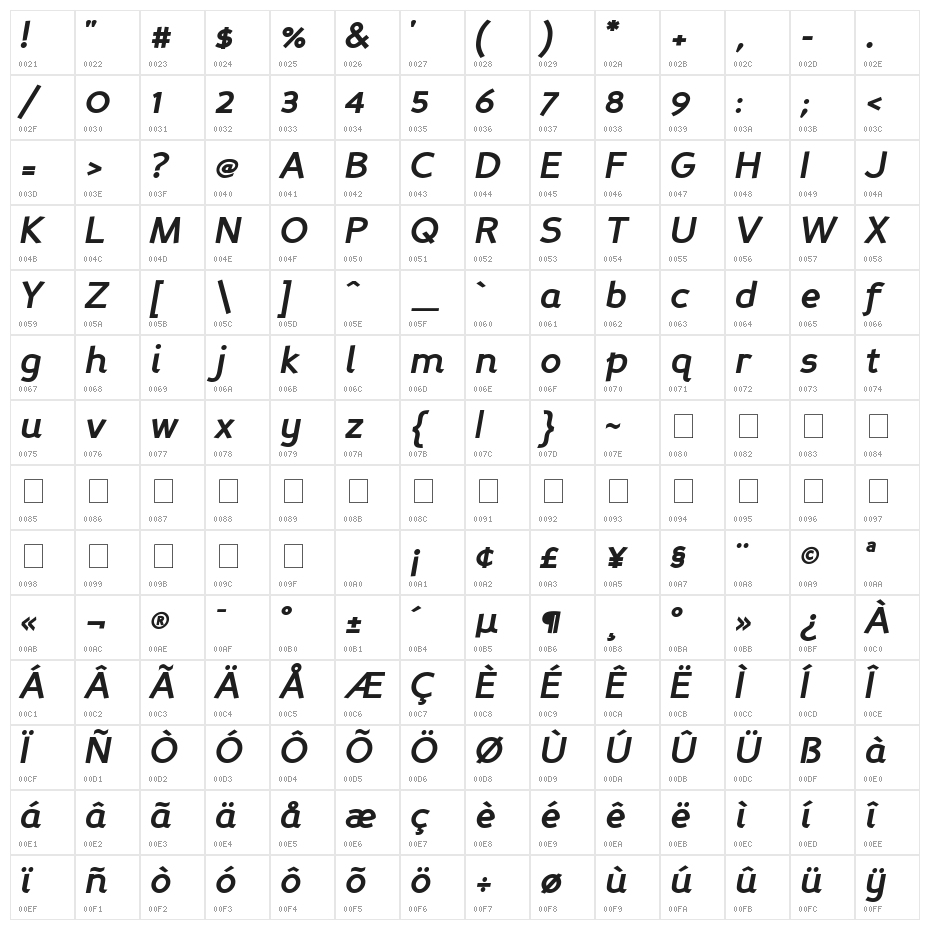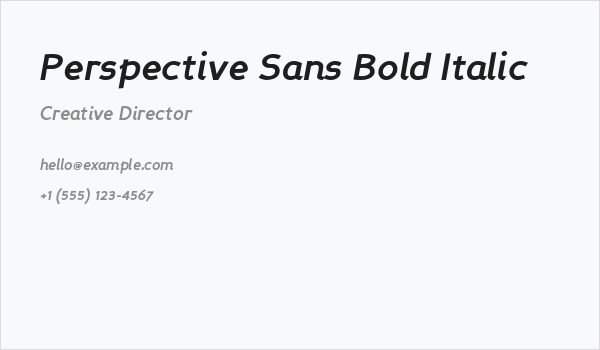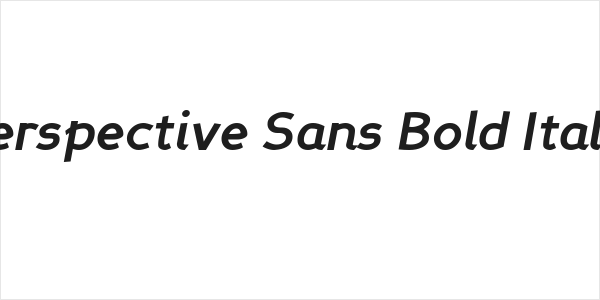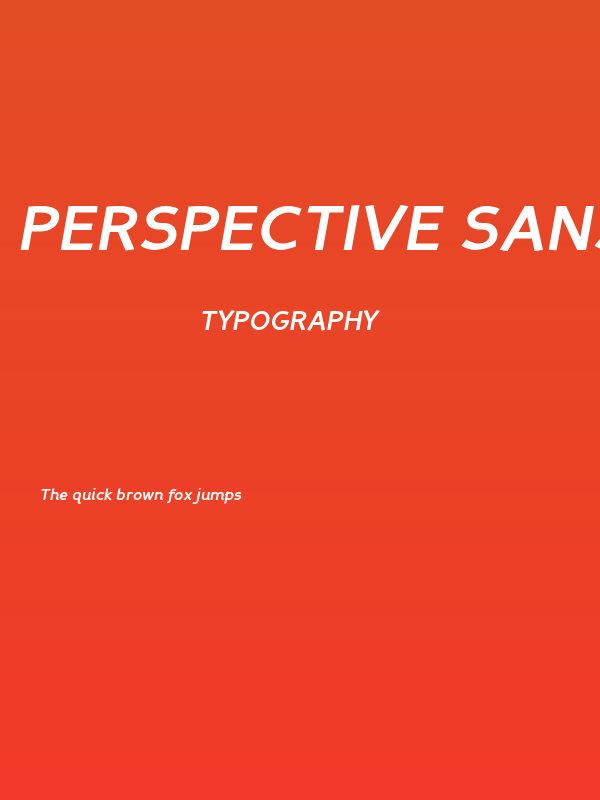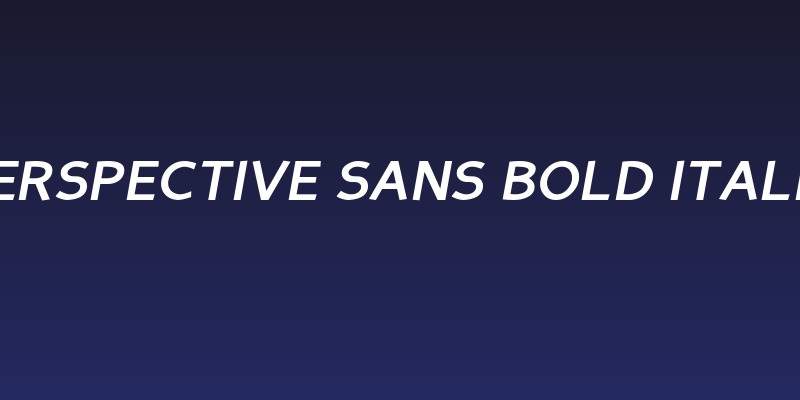
Perspective Sans Bold Italic Font
Questo font include 258 caratteri. Clicca su un carattere per vedere i dettagli.
| Caso d'uso | Headlines, Logos, Digital Media |
| Progetti proposti | Ideal for branding, advertising, digital media, and editorial design projects that require a modern and bold aesthetic. |